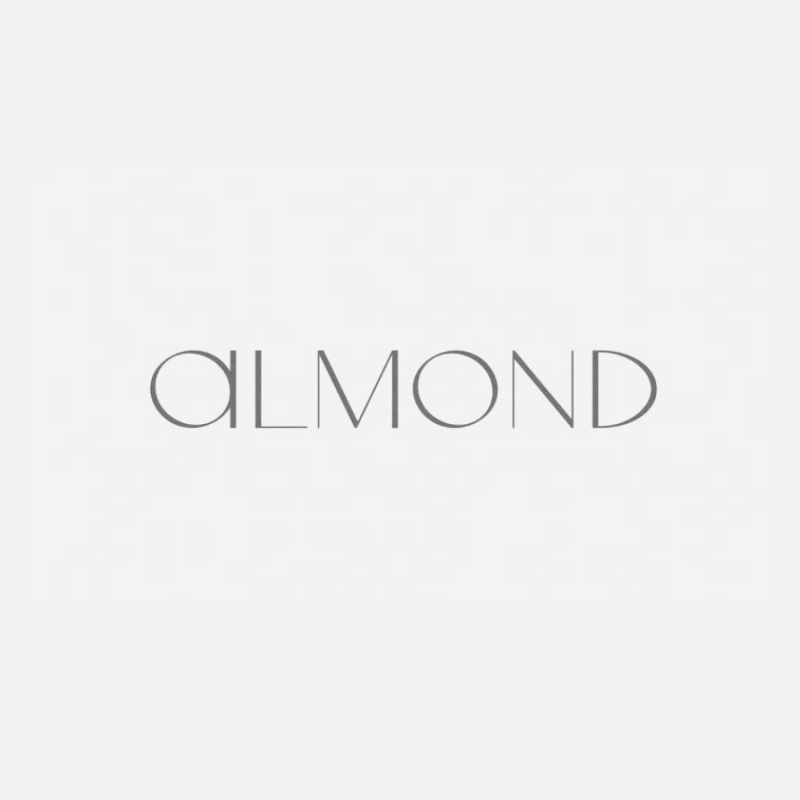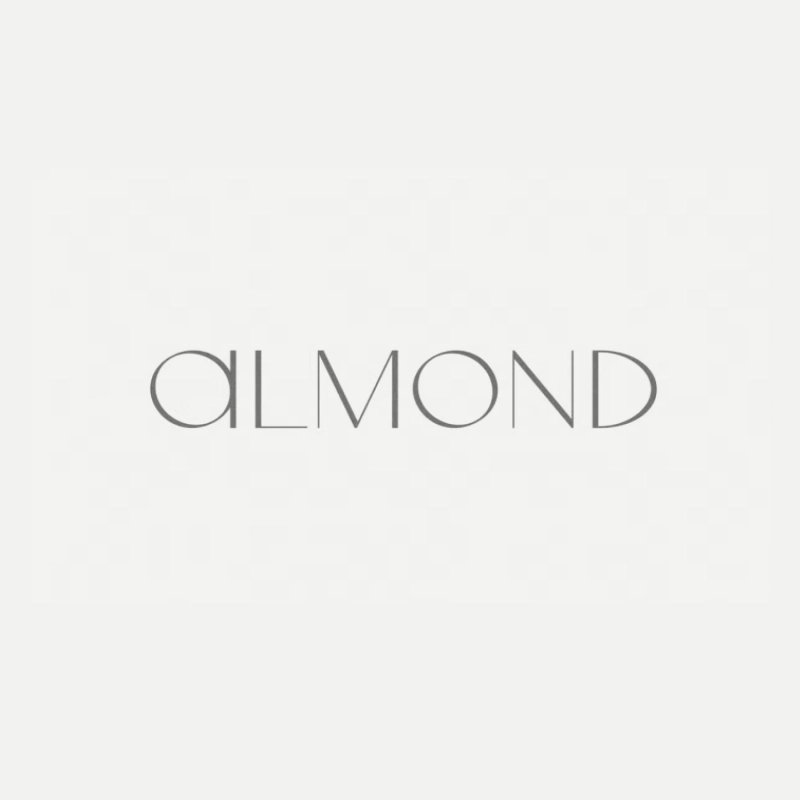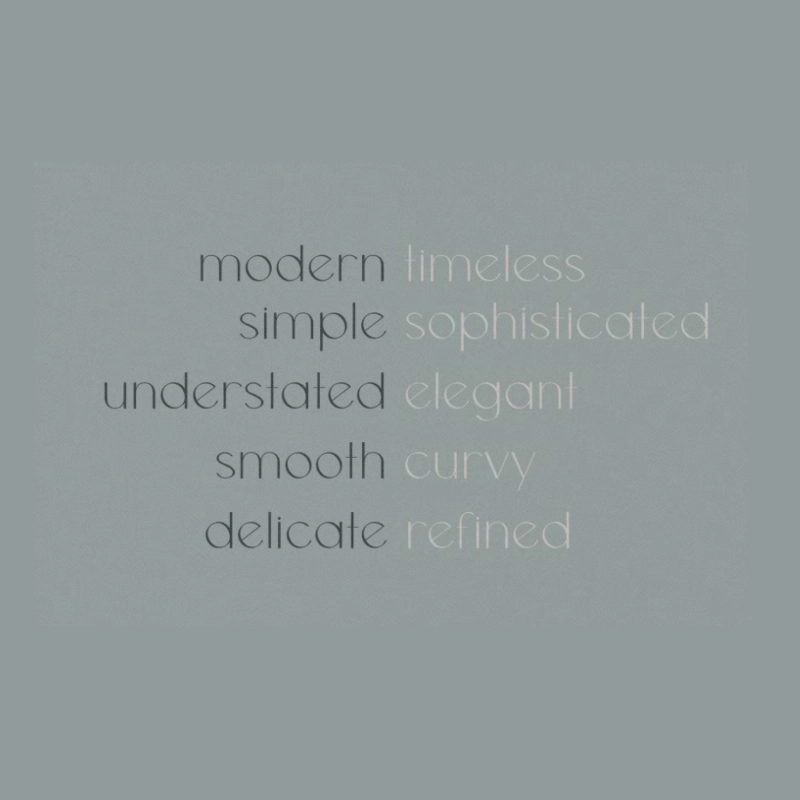
اللوز | خط بلا شريف
إنها أنيقة ، إنها متعرجة ، إنها ناعمة الزبداني. بساطتها تنضح بالرقي. اللوز هو خط عرض sans-serif مع خطوط نظيفة وضربات تباين توقف التمرير.
مثالي للشعارات والعلامات التجارية والأحرف والملصقات ورؤوس مواقع الويب والعناوين الفرعية والدعوات والتصميم التحريري والمزيد. يقترن بشكل جميل مع الحد الأدنى من سان serifs والنصوص الكلاسيكية.